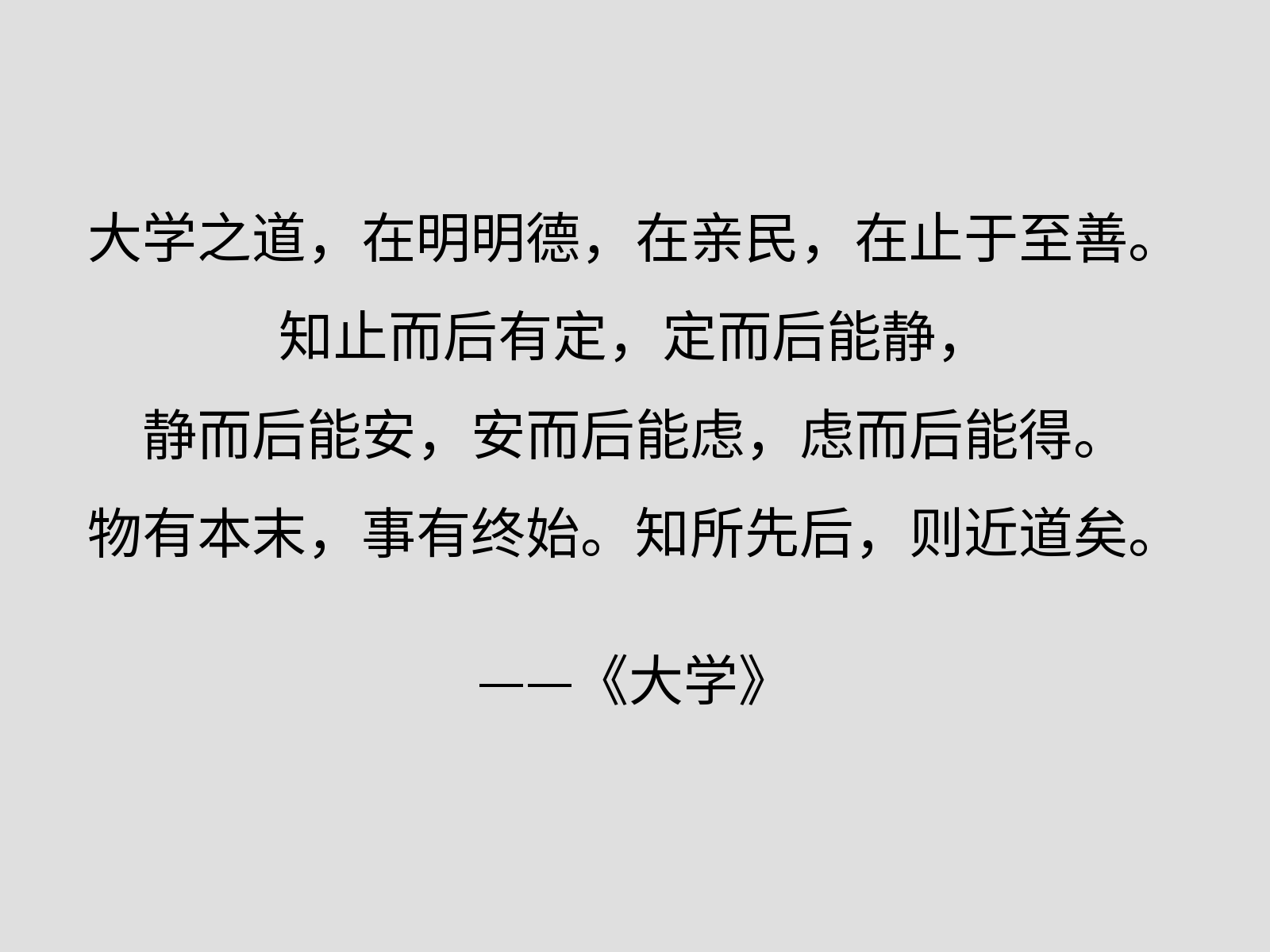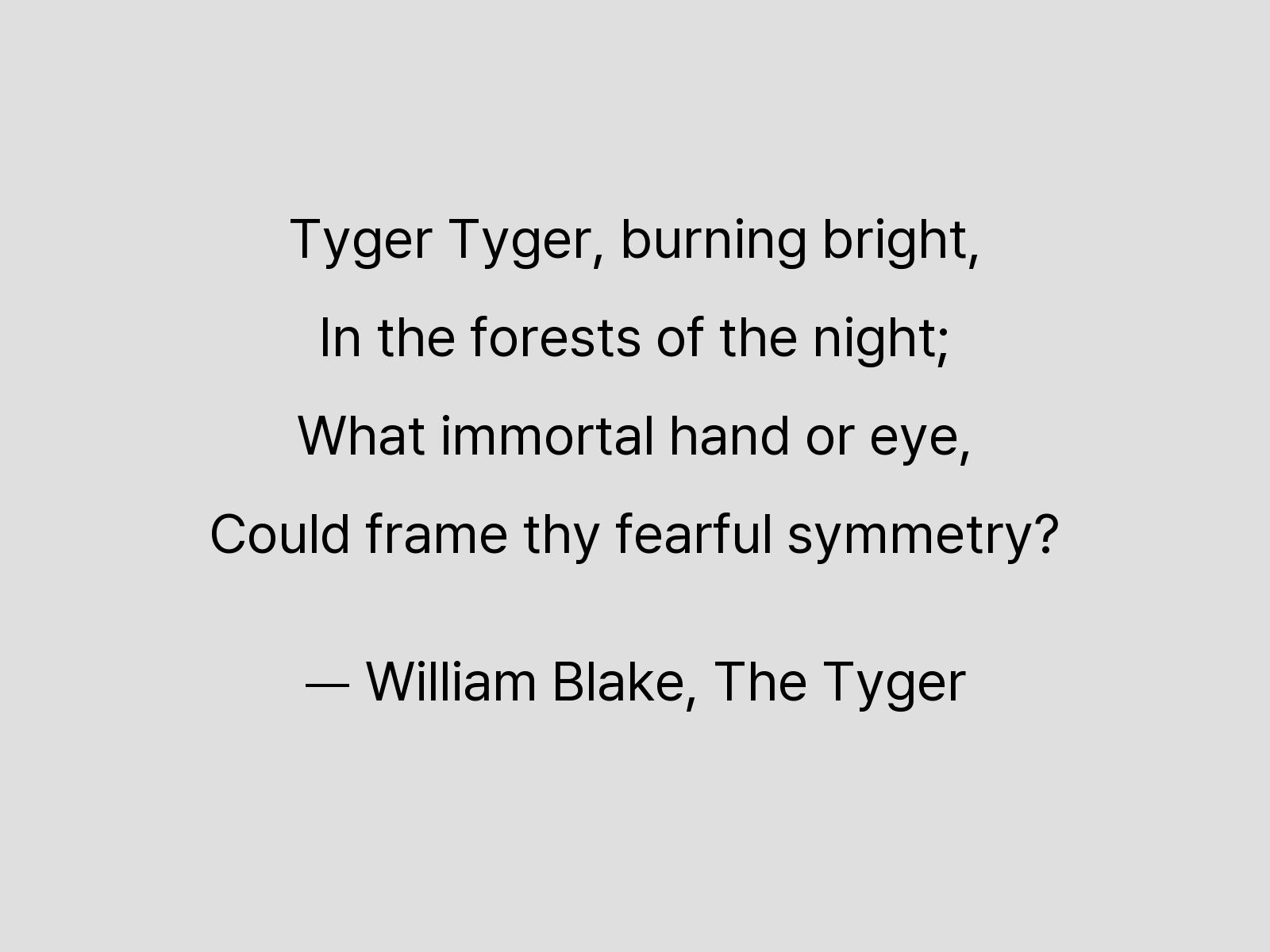
檎风黑体,基于 Pretendard Std、思源黑体和昭源黑体,商用免费的 CJK 字体。
受到更纱圆纪黑体的启发(该字体旨在参考 San Francisco,还原更纱黑体的 G 为 Inter 原版样式),将 Inter 替换为 Pretendard Std。Pretendard 由 Kil Hyung-jin(길형진)设计制作,该字体将 Inter 斜切的文字改为平切设计,使之更像 San Francisco 字体。
提供檎风黑体 Alt,可轻松区分 I 和 l,并采用等宽数字和全角引号。
- 风格
檎风黑体: 使用 Pretendard Std 原版样式檎风黑体 Alt: 区分I和l,采用等宽数字和全角引号
- 更纱黑体(构建字体)
- 思源黑体(CJK 部分)
- 昭源黑体(
CHT版本 CJK 部分) - Pretendard Std(西文)